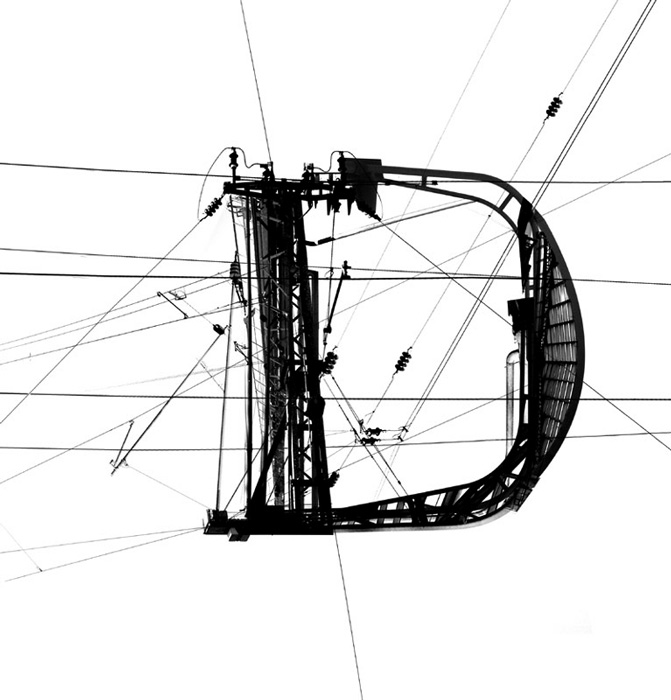
“Quick and fun experiment done with Processing: the first 3,000 characters of “Alice in Wonderland”, mapped to a cylindrical surface and rendered with varying radius and rotation properties.”
Garamond Powerline by Daniel Adolph who has created a new type inspired by well-known Garamond, and using powerlines to form letters.!